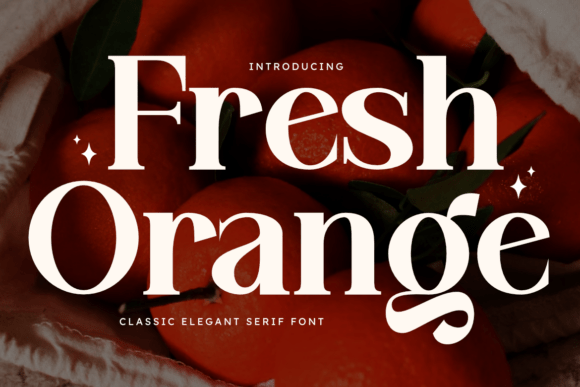
Fresh Orange
適切なデザイン要素を見つけるのは難しい場合がありますが、Fresh Orangeは作品を即座に引き立てる優れたコレクションを提供します。
精密に作られたFresh Orangeは、クリーンなベクター、滑らかなタイポグラフィ、そして安心のための商用ライセンスを提供します。
POD(オンデマンド印刷)製品、結婚式の招待状、またはソーシャルメディアのグラフィックを作成している場合でも、Fresh Orangeは理想的です。